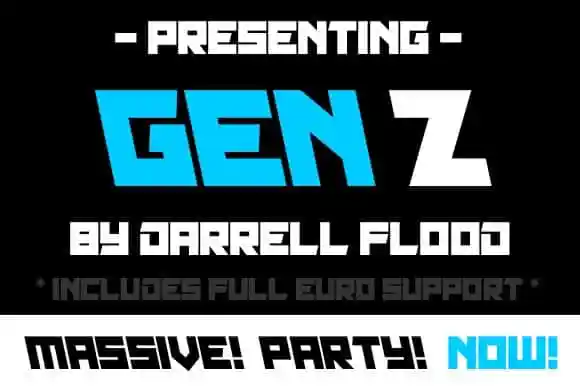
A fonte Gen Z Display é uma escolha perfeita para quem busca imprimir sua marca com um toque inovador e vibrante. Com seu forte tema esportivo e estilo futurista, esta fonte moderna e bold certamente se encaixa em criações que precisam de um destaque imediato. É ideal para estilos tecnológicos ou científicos, mas também é perfeita para quem deseja dar um toque atraente às suas propostas criativas. A Gen Z Display, criada pelo designer Dadiomouse no site 99designs, é uma excelente opção se você está procurando por um efeito visual inovador para seus projetos digitais ou impressos. Não perca tempo com algo que já é óbvio – a Gen Z Display traz um toque único e moderno à sua identidade visual.